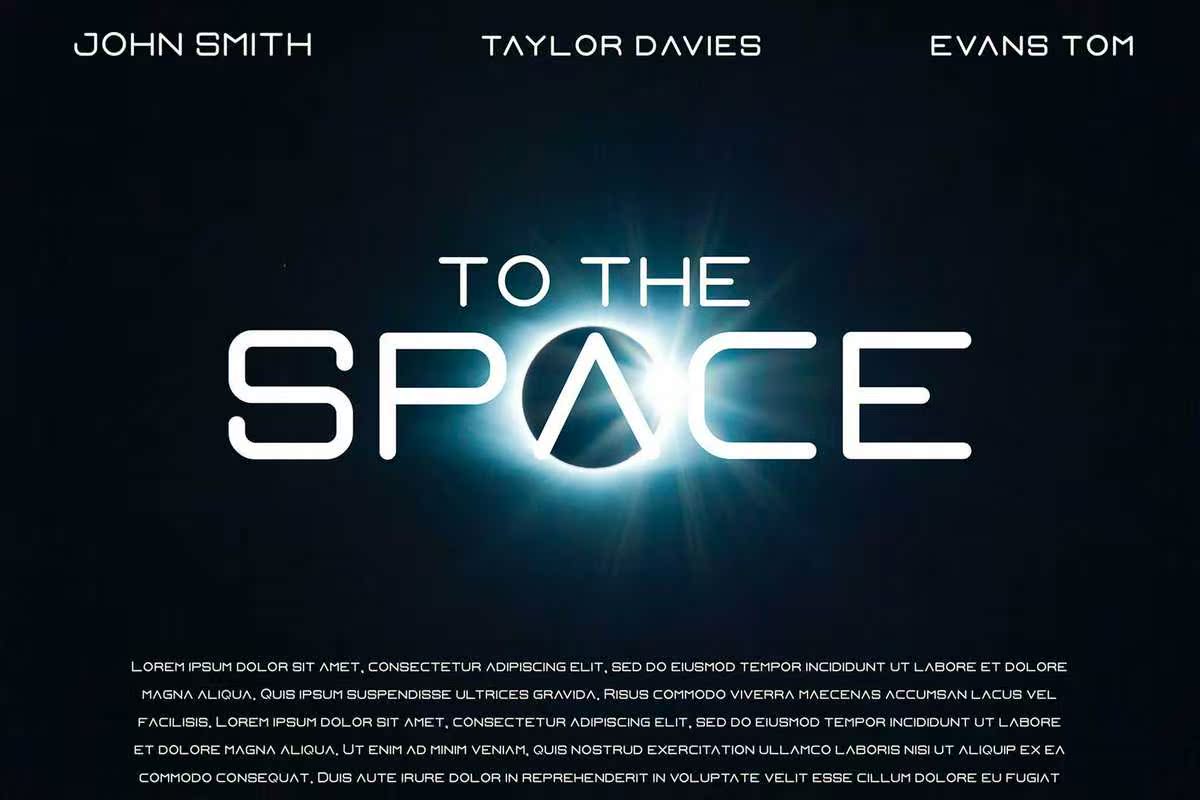
钢铁般的现代化和开放式建筑,将永远带走你的未来!Steelrwill以其粗体、yetconceptualstyle的风格在众多项目中大放异彩,让您的文字脱颖而出!钢铁般的现代化和开放式建筑,将永远带走你的未来!Steelrwill以其粗体、yetconceptualstyle的风格在众多项目中大放异彩,让您的文字脱颖而出!